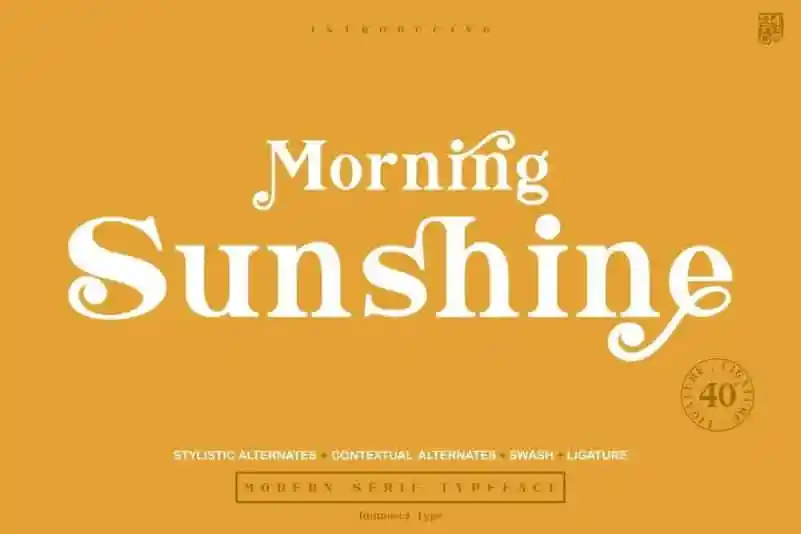
Morning Sunshine Serif Font – Download Grátis
A Morning Sunshine Serif Font é uma descoberta para criativos que buscam uma mistura perfeita entre clássica tipografia e nuances modernas. Inspirada no estilo serif clássico, esta fonte se destacou por adicionar detalhes suaves aos finais de linhas (serifs) que tornam a leitura ainda mais legível em tamanhos menores. O design é tão atraente quanto funcional, pois inclui recursos OpenType como ligaturas, alternativas contextualas e estilísticas para acessar uma gama vasta de variações e até mesmo swashes, criando um tipo muito leve que se adequa perfeitamente aos mais diversos projetos. Seja para revistas, marcas, camisas, cartões de aniversário, logotipos ou qualquer outra necessidade de design, esta fonte é uma escolha inteligente para capturar atenção e transmitir mensagem com estilo. A Morning Sunshine Serif Font oferece a versatilidade necessária para traduzir suas ideias em projetos criativos, tornando-a um aliado valioso em qualquer esforço de design gráfico.